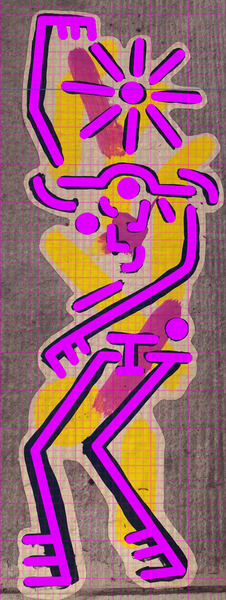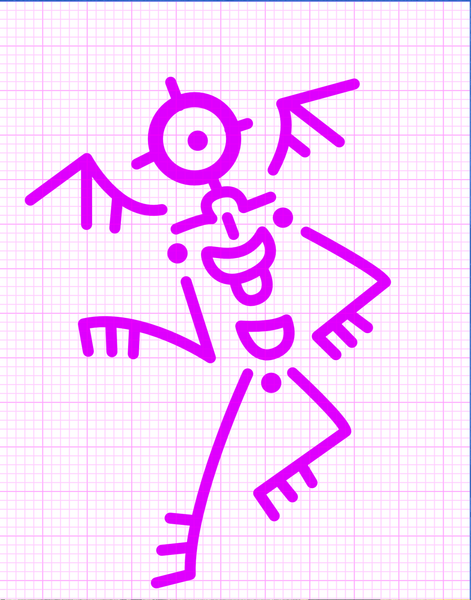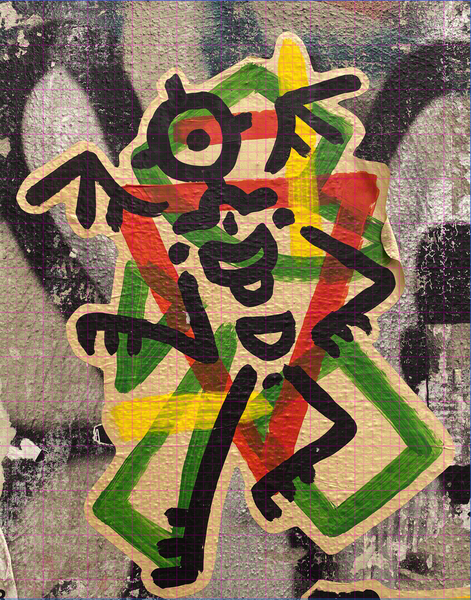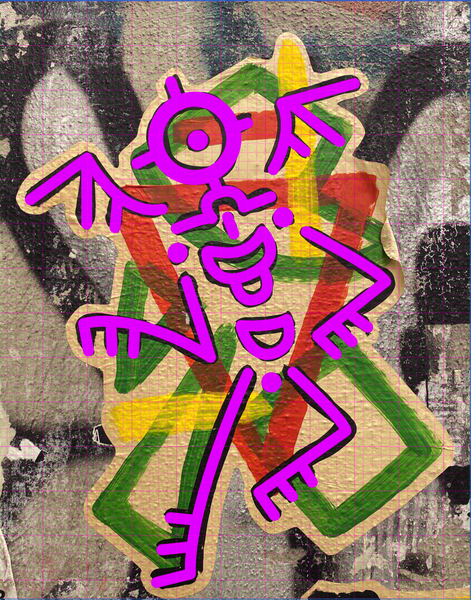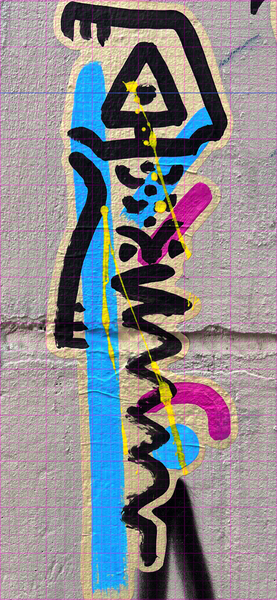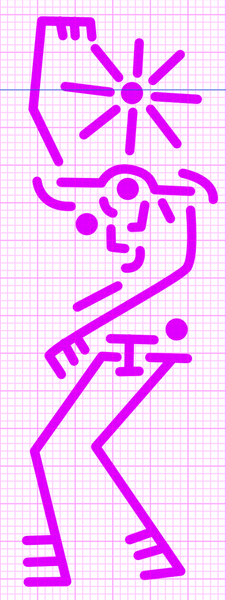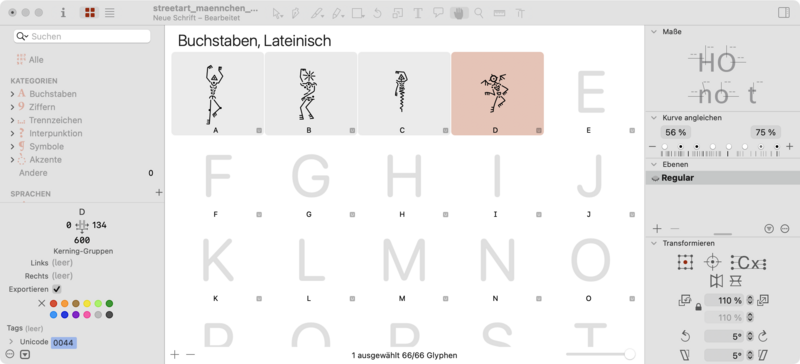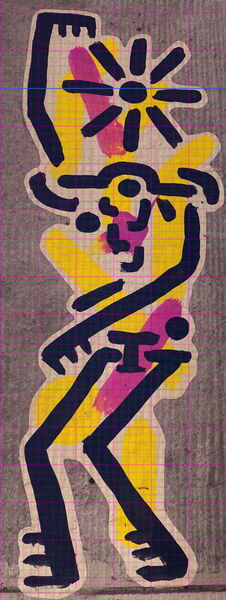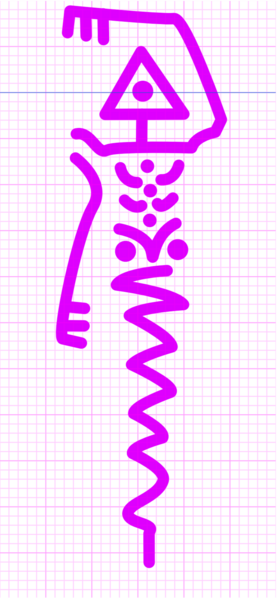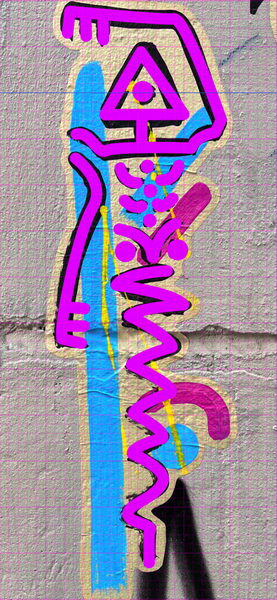
Dingbats-Schrift - Streetart-Männchen Teil 1
In der Neustadt und im angrenzenden Hechtviertel in Dresden gibt es eine sehr lebhafte Streetart-Szene. Einen Überblick zeigt meine Streetart-Webseite.
Im Navigationspunkt „Paste-Up” auf dieser Seite sind auch lustige Strichmännchen zu sehen. Diese kommen wie Skelette daher und sind oft noch farbig unterlegt. Ich kenne den Streetart-Künstler nicht. Aber die Paste-Up-Graffitis haben eine erstaunliche Formenvielfalt. Die Männchen habe ich nun zum Thema des ersten Dresdner-Streetart-Font auserkoren.
Für den Start habe ich vier relativ ähnliche und typische Figuren ausgesucht. Die Fotos wurden in eine Vektorgrafiksoftware  importiert und in eine vergleichbare Größe skaliert.
Danach kam der schwierigste Teil des Starts. Es musste eine für das Nachzeichnen geeignete Strichstärke festgelegt werden. Da die Paste-Up-Graffitis mit einem Pinsel gemalt sind, variiert die Strichstärke der Männchen je nach dem, wie stark mit dem Pinsel aufgedrückt wurde.
Trotzdem sind die so entstandenen Vektorzeichnungen sehr fein. Zum Schluss wurden alle Vektorstriche mit dem Befehl „Kontur erweitern” in Flächen umgewandelt, so dass sie in den Fonteditor exportiert werden konnten.
Diese ersten vier Männchen bilden den Start für die Dingbats-Schrift.
Sicherlich ist die entstehende Schrift nichts für kleine Schriftgrößen. Aber ab einer Schriftgröße von 28 pt kann man die lustigen Männchen gut erkennen.
Hier einige Bilder von den ersten Arbeitsschritten: